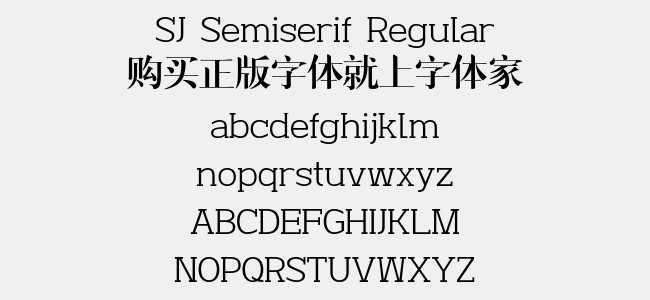
SJ Semiserif Regular
字体作者:三极字库
字体名称:SJ Semiserif Regular
字体字数:26个英文大小写字母及和阿拉伯数字
字体家族:三极系列
书体类型:英文类
字体公司:三极系列
SJ Semiserif Regular
SJ Semiserif Regular - 大写字母/小写字母/数字